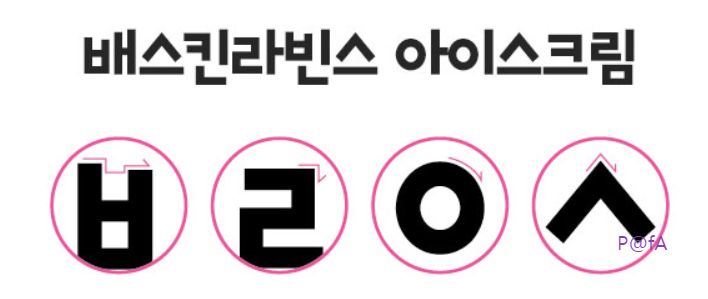
배스킨라빈스 특유의 개성을 담아 한글날 기념으로 제작한 배스킨라빈스체를 무료로 다운로드하는 방법을 살펴본다. 더불어 누구나 무료로 사용이 가능한 배스킨라빈스체를 컴퓨터에 설치하는 방법과 코딩 시에 사용하는 방법도 살펴본다.
배스킨라빈스를 운영하는 (주)비알코리아에서 2018년에 한글날을 기념하여 제작한 배스킨라빈스 전용 서체인 배스킨라빈스체는 누구나 사용 가능한 무료 폰트로 배포하고 있다. 단, 제작 후에 배스킨라빈스 홈페이지에서 무료로 다운로드할 수 있는 링크를 제공했지만 현재는 홈페이지 업데이트 후에 해당 다운로드 링크를 찾을 수 없는 상태이다.
배스킨라빈스체는 위의 이미지에서 보듯이 음소 자체의 획이 지닌 높낮이를 변형해서 배스킨라빈스의 주력 상품인 아이스크림 특유의 리듬감을 표현하고 있다.
이렇듯 배스킨라빈스체는 다양한 아이스크림 플레이버 리드감을 초성의 세로획과 가호뢱의 높낮이 차이와 함께 들쭉날쭉한 받침으로 표현함으로써 유쾌하고 통통 튀는 귀여운 형태를 연출하고 있다.